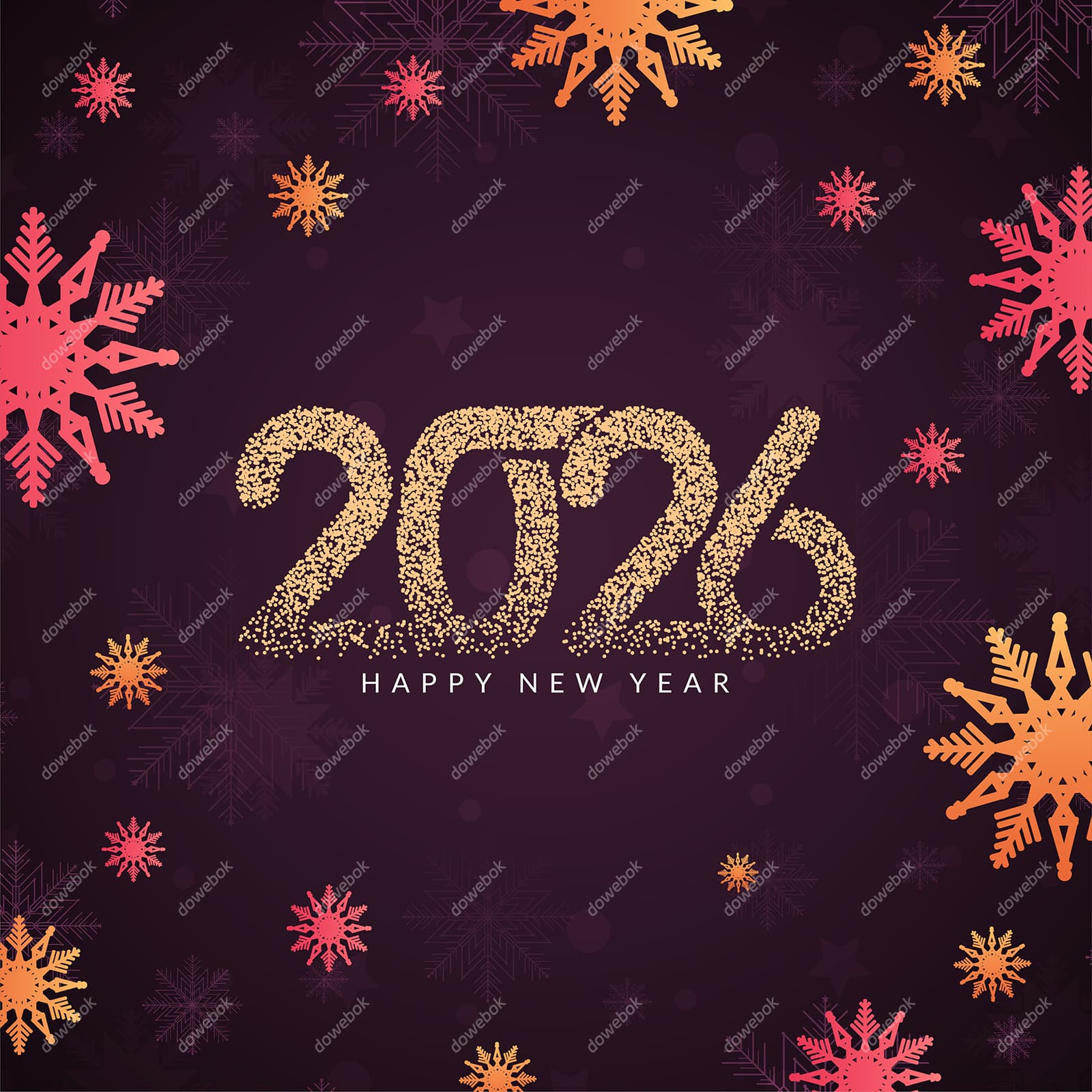
这是一款多彩雪花和金色颗粒数字设计 2026 新年快乐矢量素材,深紫背景上,粉橙雪花装饰错落分布,深浅纹理添冬日氛围。“2026” 以金粉颗粒拼接而成,质感细碎灵动。下方衬着简约黑体 “Happy New Year”,整体以暖调色彩 + 雪花元素,既显冬日跨年的温馨感,又用颗粒字体透出精致俏皮的节日气息。